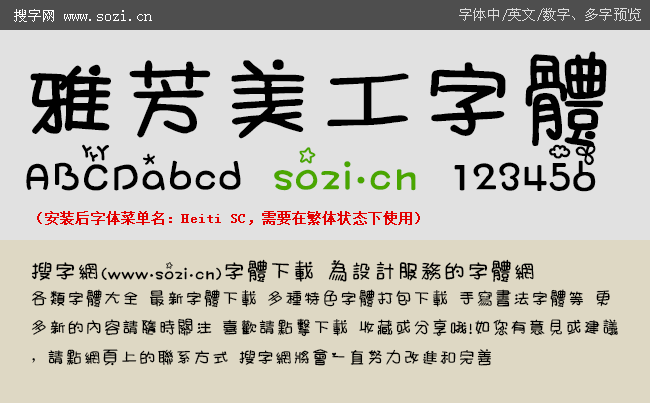
雅芳美工字體
搜字網(wǎng)給大家提供一款卡通手寫風(fēng)格的手機(jī)中文字體下載。名字叫雅芳美工字體,這款手機(jī)字體是仿照兒童手寫風(fēng)格的卡通手寫字體,結(jié)構(gòu)帶有POP字體風(fēng)格,字體間還插入有趣的卡通圖案,特別適合喜歡手機(jī)字體個性一些的朋友在手機(jī)上安裝使用。